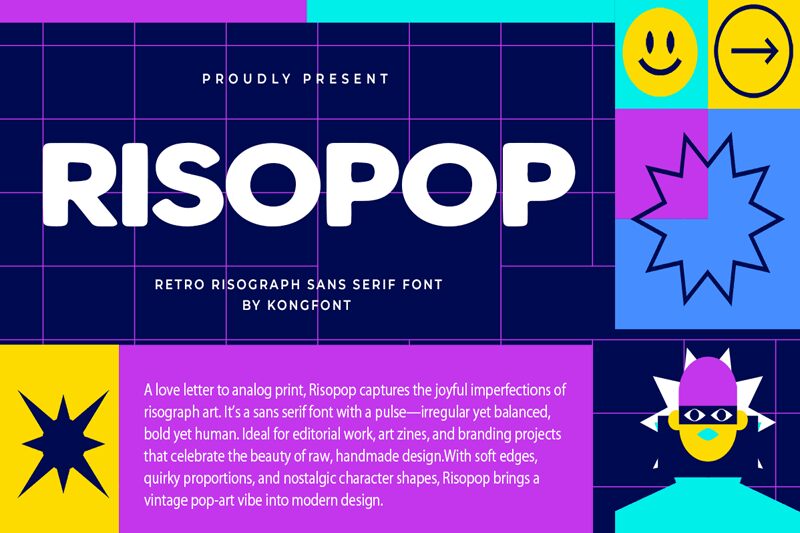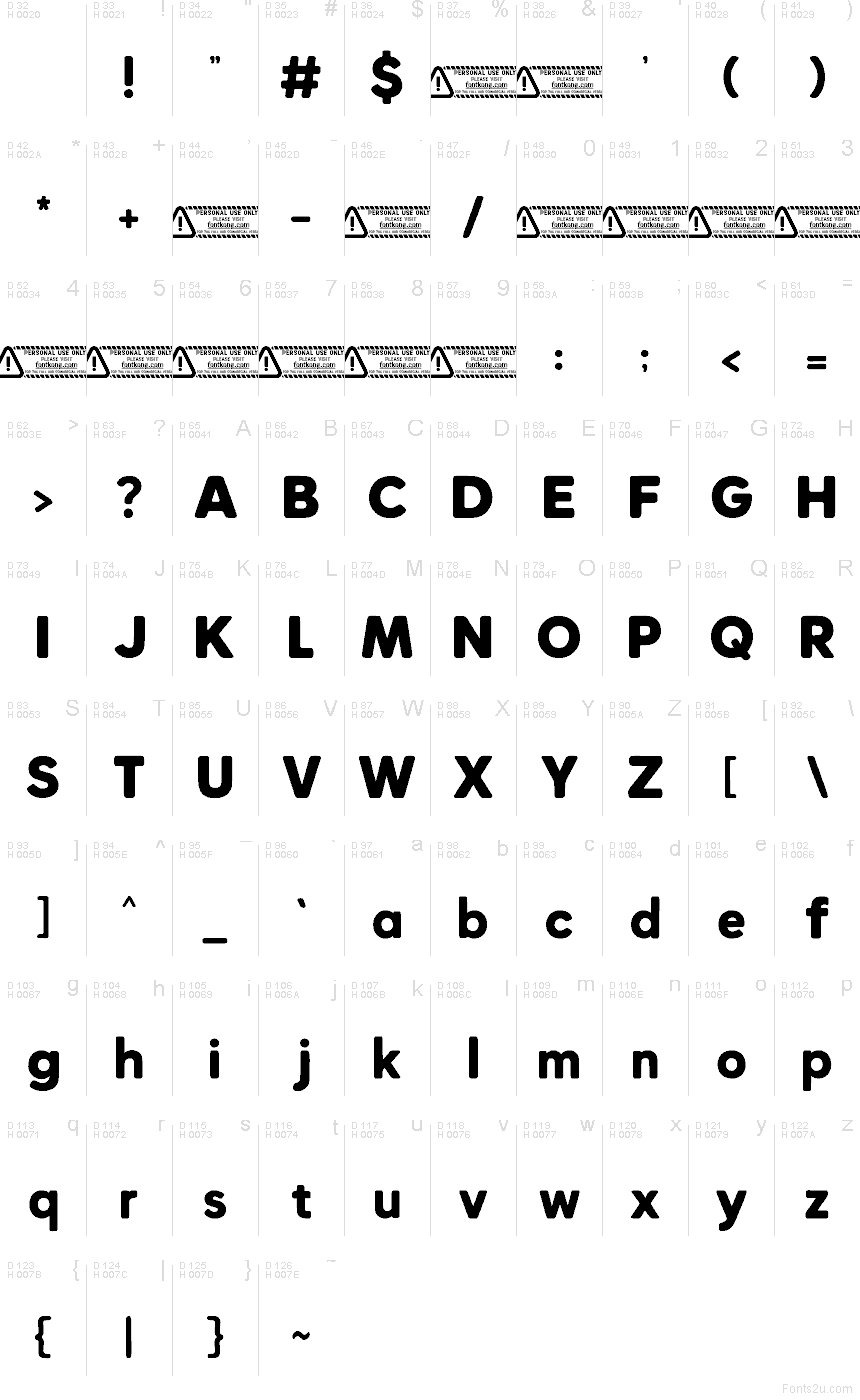
Risopop di Kong Font è un carattere sans serif gratuito in stile chunky, caratterizzato da forme morbide e arrotondate che evocano la consistenza di un timbro in spugna appena inchiostrato. Il suo ritmo ampio e circolare garantisce un'ottima leggibilità anche nelle parole lunghe, conferendo al contempo un tocco vivace che rende amichevoli anche i titoli più d'impatto. Il suo peso è deciso senza risultare rigido, permettendo ai titoli di posarsi sulla pagina con una morbida naturalezza.
Risopop è perfetto per dare personalità immediata a poster, adesivi, packaging per bambini, annunci social, miniature YouTube, volantini per eventi e loghi giocosi. Questo font gratuito brilla nei grandi formati, specialmente se lasciato respirare; prova ad abbinarlo a un carattere sans serif sobrio e sottile per i testi secondari, per evitare un effetto troppo vivace.